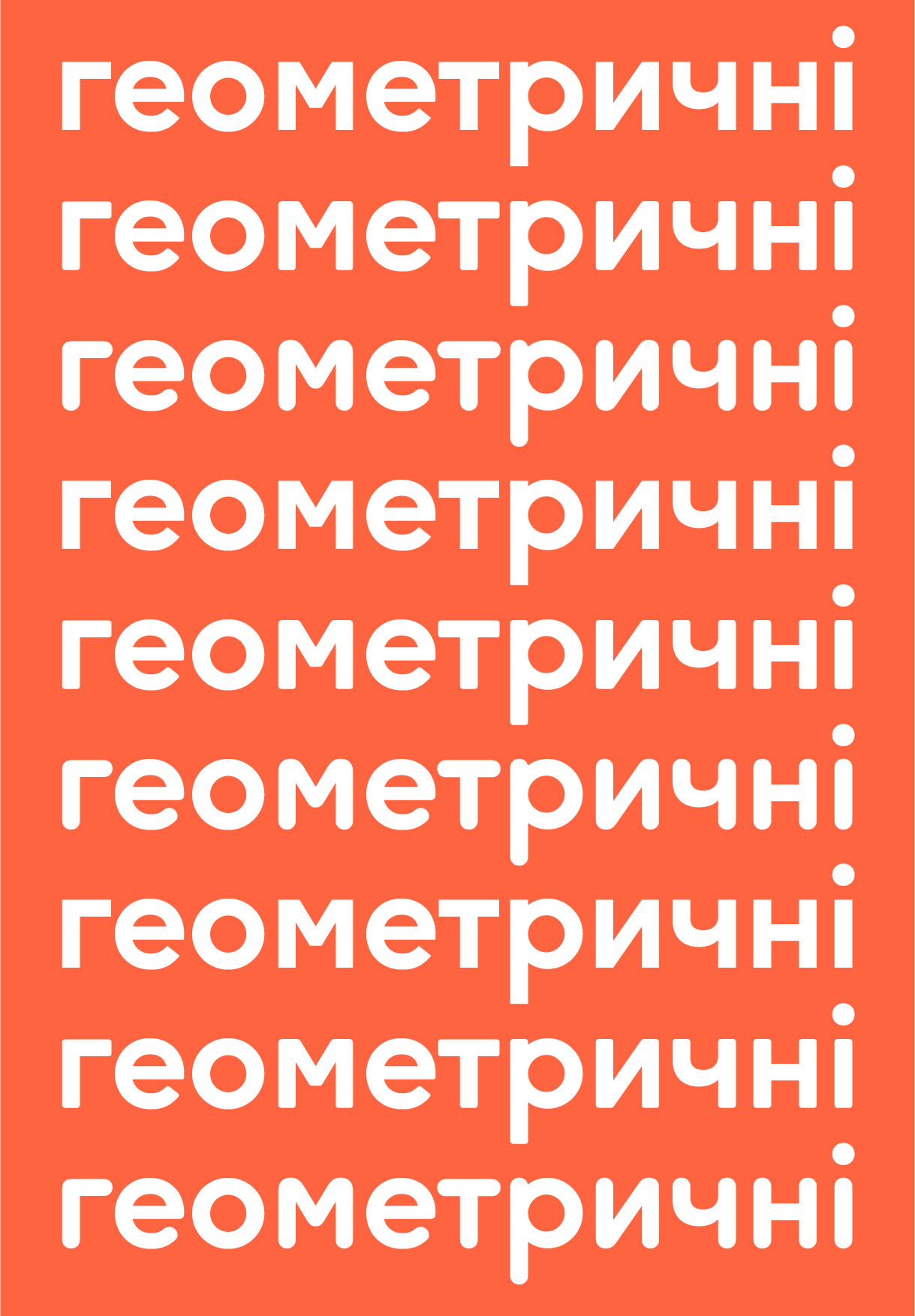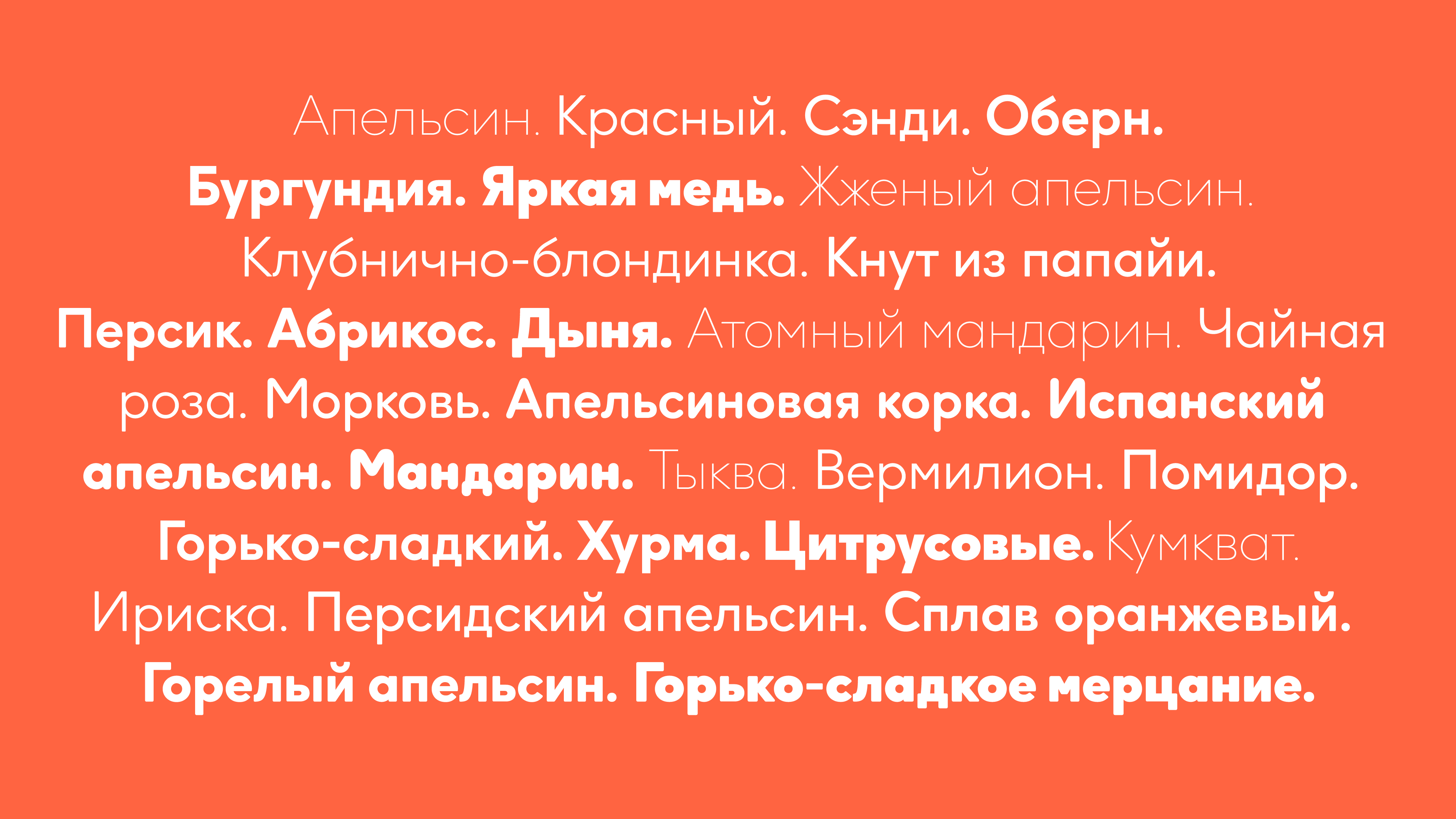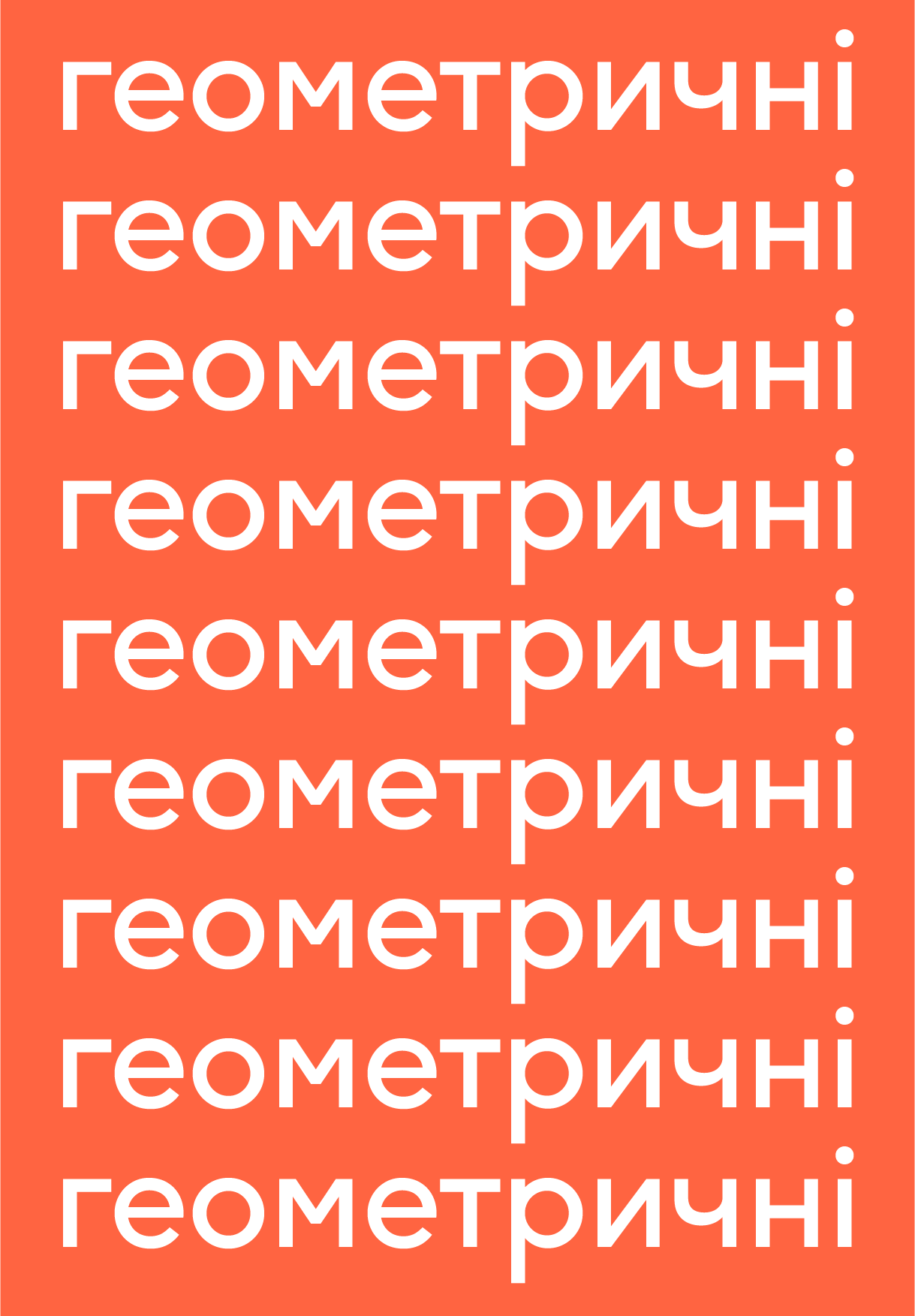
F37 Ginger Cyrillic Font Sampler
Геометрические формы F37 Ginger и необычные, почти круглые стойки делают его идеальным выбором для логотипов и заголовков.